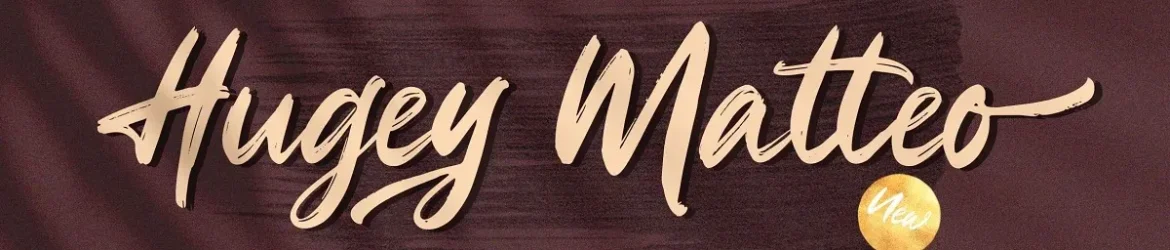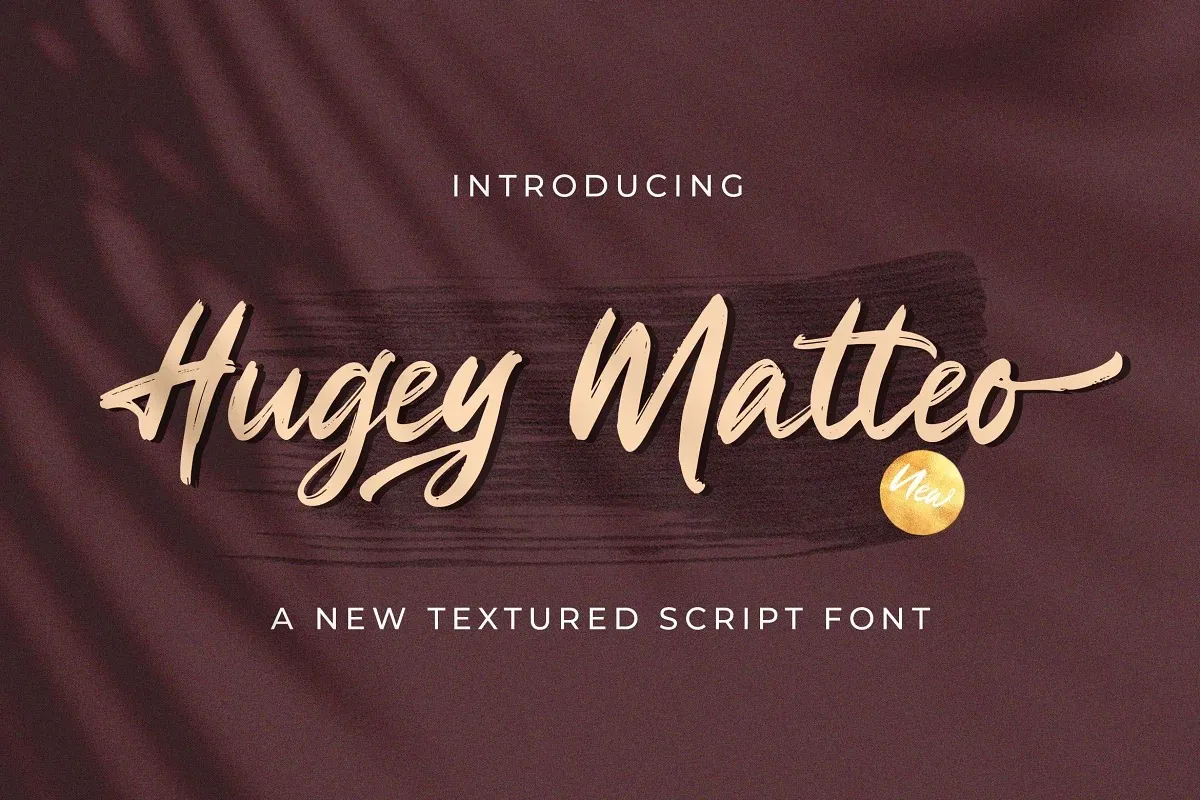
Hugey Matteo Font
Esta é uma fonte de traço feito à mão criada pela StringLabs, com um charme único e incrivelmente adaptável a diversas aplicações design. Perfeita para qualquer tipo de marca, embalagem de produto, convite, citação, t-shirt, etiqueta, brochura ou logomarca que deseje criar. Ideal tanto para designers profissionais quanto para iniciantes, esta fonte doce e sofisticada se destaca por sua capacidade versátil. É perfeita para quem busca um toque único em suas criações visuais, seja ela uma marca de sucesso ou um design gráfico elegante. Perfecto para quem deseja dar vida aos seus projetos de uma maneira única, criando designs inovadores e impecavelmente cuidadosos.